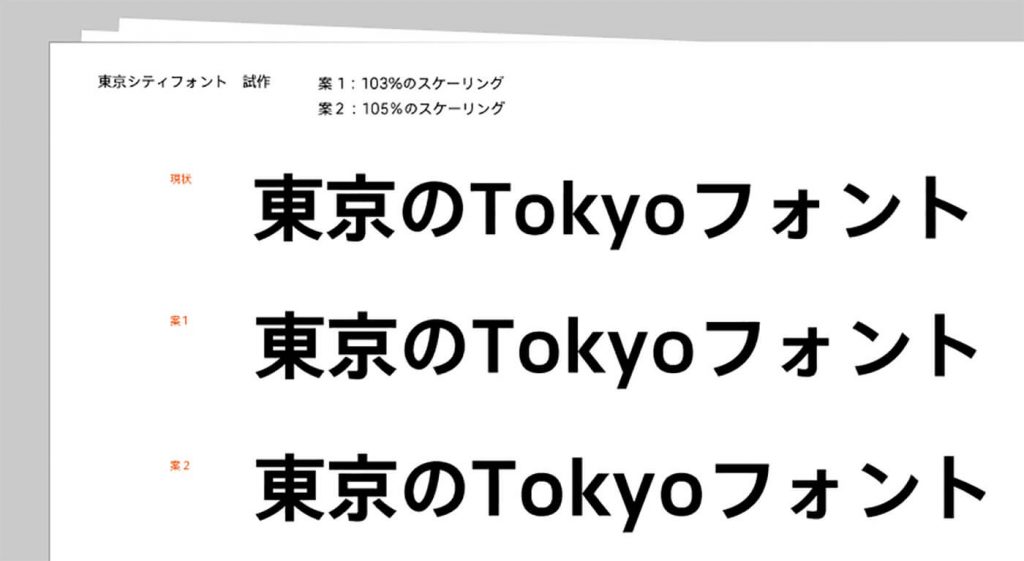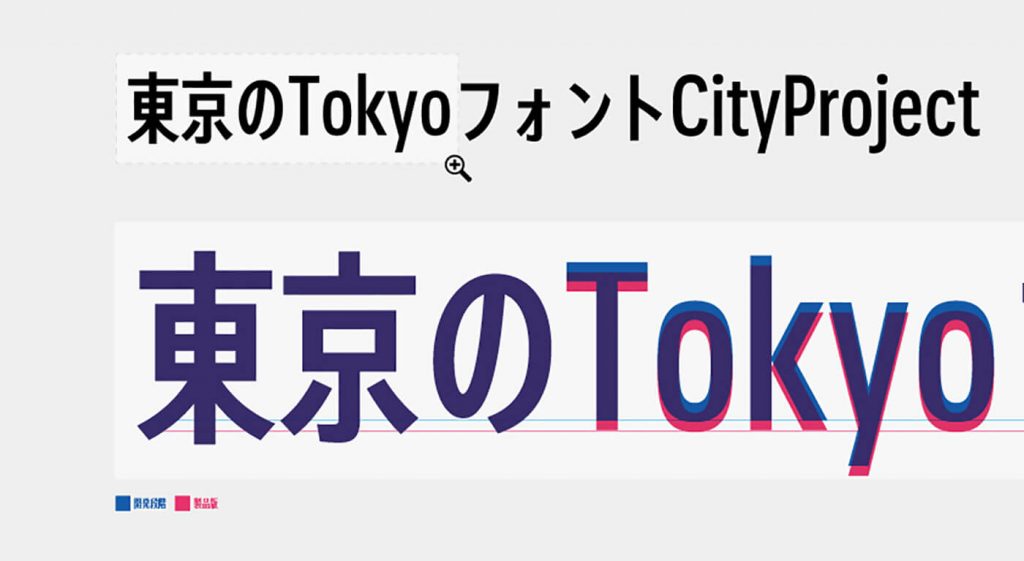
東京シティフォント開発ストーリー02「和文との調和」
和文はTPスカイローコントラストを採用しています。欧文のコンセプトとデザインがある程度固まったところで、和文との調和をとる作業が始まります。試作段階では欧文が小ぶりに見えたため、さまざまな大きさを試し、最適なサイズを探りました。
また、字幅の狭い文字に取り掛かった際には、そのまま欧文を組むと少し上がって見えてしまうという問題点がありました。それを解決するため、欧文を下げることで自然に見えるように様々な検証を行いました。最終的にはベーシックを1%、コンデンスを2%、コンプレスを3%下げ、そのまま利用しても調和が取れるようになっています。
さまざまな検証を経てリリースされた東京フォントは15フォントのファミリー構成により、空間に応じて必要な情報を効率よく、読みやすく表示することが可能なフォントです。これから幅広い場所でこのフォントが見られたら良いなあ、と思っています。